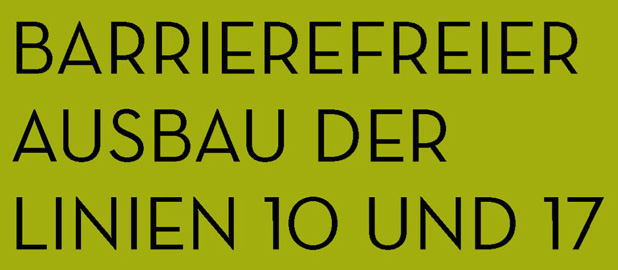
Was ist das, Mischung aus Futura und Gill Sans
meine Schriftidentifizierung versagt bei diesem Beispiel, bei dem ich nur Großbuchstaben habe. Es sieht aus wie eine Mischung aus Futura und Gill Sans, mit etwas Einschlag bei den 20er-Jahre-Schriften. Merkmal ist das sehr bauchige R und die heruntergezogene Mittellänge. Wer etwas dazu weiß, bitte melden. :huhu: